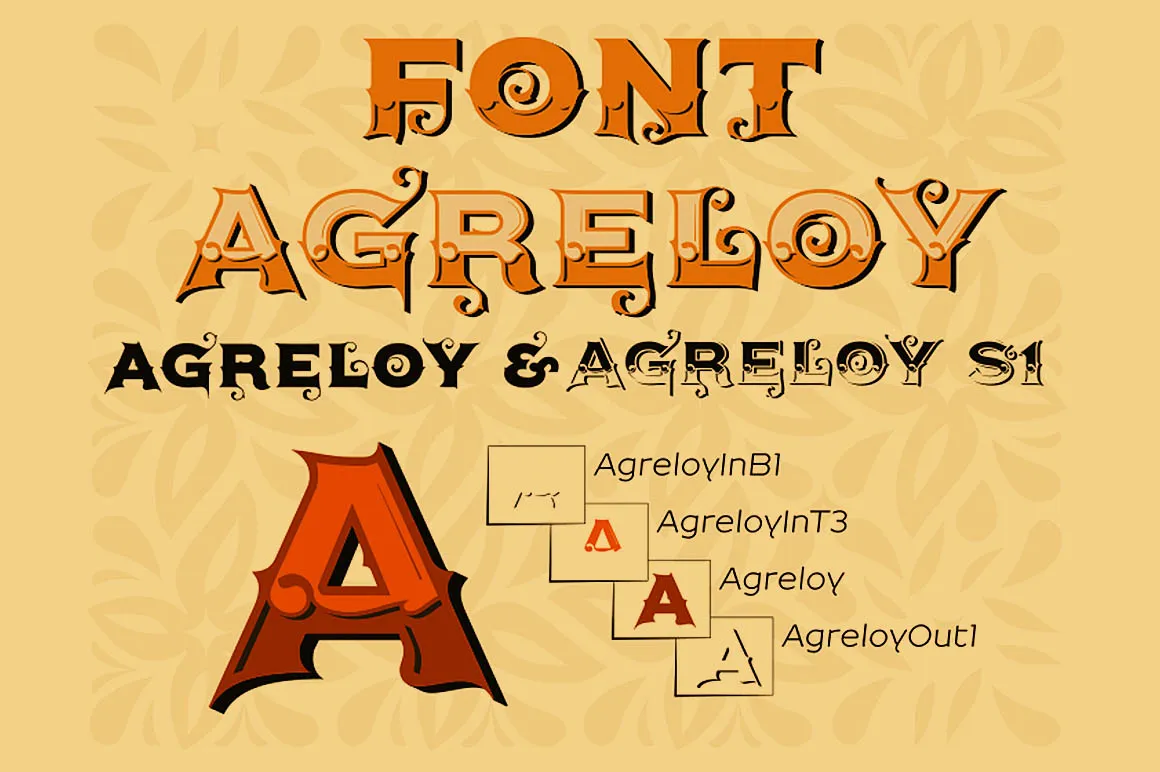
Agreloy Font Family – Download Grátis
A Agreloy Font Family é uma escolha perfeita para qualquer projeto que valoriza estética limpa e moderna. Embora seja classificada como Gothic fonts, sua natureza dinâmica oferece um toque de sofisticação que vai alem da categoria convencional. Inspirado pelo designer Hamilton, essa fonte traz uma versão do seu universo visual, combinando formas retas com detalhes suaves e harmoniosos. Ideal para aplicativos digitais ou criações gráficas, esta família de fontes combina elegância minimalista com um toque de energia moderna. Suas linhas finas e precisas ajudam a criar um design sólido em qualquer plataforma digital, enquanto seus traços leves proporcionam uma experiência visual confortável para o usuário final. Seja você criando um site clean, produzindo material gráfico ou desenvolvendo aplicativos de alta performance, a Agreloy Font Family é um recurso valioso que não apenas preenche suas necessidades estéticas, mas também ajuda a garantir uma experiência de uso fluida e profissional.